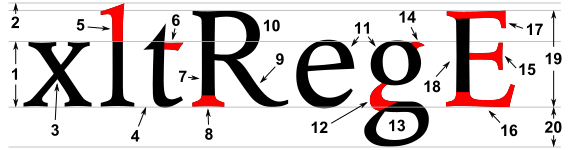
Линии
Через любую строку текста можно провести несколько воображаемых горизонтальных линий:
- Верхний край кегельной площадки — в металлическом наборе является верхней границей литеры. В компьютерных шрифтах верхний край кегельной площадки первой строки является верхним краем блока текста. В некоторых шрифтах, чаще всего декоративных, выносные элементы могут выходить за пределы верхнего края кегельной, однако такие выносные элементы требуют специальных инструкций для сопряжения с элементами верхней строки, во избежание наложений. Расстояние от верхнего до нижнего края кегельной площадки называется кеглем шрифта[1];
- Линия верхних выносных (2) — линия, проходящая через вершины верхних выносных элементов, если они унифицированы по высоте. В некоторых шрифтах может совпадать с линией прописных, но чаще — выше её[2];
- Линия прописных — линия, проходящая по верхней границе прописных букв[3]. Расстояние от базовой линии до линии прописных называется ростом прописных (19);
- Линия строчных — линия, проходящая по верхней границе строчных букв, не имеющих верхних выносных элементов и оптической компенсации[4]. Расстояние от базовой линии до верхней линии строчных называется ростом строчных (1);
- Базовая линия (линия шрифта) (4) — линия, проходящая по нижним границам букв, не имеющих нижних выносных элементов, свисаний и оптической компенсации[5]. Базовая линия одна для прописных и строчных букв. В вариативных шрифтах базовая линия остаётся статичной, однако вертикальные метрики могут динамически изменяться[6];
- Линия нижних выносных — линия, проходящая по нижнему краю нижних выносных элементов, если они унифицированы по высоте[7]. В современной типографике линии выносных элементов могут выступать как настраиваемые оси вариативности[8];
- Нижний край кегельной площадки — нижняя граница литеры;
- Кроме горизонтальных линий, важное значение имеет ось овала — линия, проходящая вдоль наибольшего диаметра овала, либо через наиболее тонкие участки штриха. Ось овала может быть вертикальной или наклонной[9].
Штрихи
- Основной штрих (штамб) (7) — наиболее толстый вертикальный или наклонный штрих в шрифтах, имеющих контраст[10]. В вариативных шрифтах его толщина динамически изменяется при помощи оси насыщенности (wght)[8];
- Соединительный штрих — более тонкий, чем основной, горизонтальный или наклонный штрих[11]. В вариативных шрифтах соотношение его толщины с основным штрихом также может динамически управляться[8].
Выносные элементы
- Верхний выносной элемент (5) — выносной элемент строчной буквы, выступающий вверх за линию строчных;
- Нижний выносной элемент — выносной элемент, свисающий ниже базовой линии;
- В вариативных шрифтах высота верхних и нижних выносных элементов может управляться через пользовательские оси вариативности, что позволяет адаптировать шрифт под конкретные задачи вёрстки[8].
Прочие элементы
- Вершина (апекс) (3) — соединение двух наклонных штрихов либо наклонного и вертикального штриха, образующее угол либо имеющее ровную площадку[12];
- Горизонтальный элемент (6) — штрих, расположенный поперёк вертикального штриха. Может быть соединён с ним по краям либо в середине[13];
- Овал — округлый элемент штриха замкнутой формы, например в буквах «О», «Ю». Ось овала может быть прямой или наклонной[14];
- Полуовал (10) — может быть как замкнутым и ограниченным с одной из сторон штрихом (в буквах «Р», «Б»), так и разомкнутым (например, в букве «З»)[15];
- Узел — соединение в одном месте нескольких штрихов[16];
- Перекладина (15) — Горизонтальный штрих примерно (оптически) на середине высоты букв[17];
- Кегельная площадка — в металлическом наборе — площадка на ножке литеры, на которой располагался отпечатываемый знак. В цифровом наборе кегельная площадка — абстрактный прямоугольник, очерченный вокруг знака[18];
- Концевой элемент — окончание штриха, не имеющее засечки[19];
- Нога (9) — Наклонный штрих, заканчивающийся засечкой или концевым элементом;
- Засечка (сериф) (8) — короткий штрих, перпендикулярный основному, расположенный на его конце[20]. В вариативных шрифтах её форма и толщина могут параметрически изменяться[21];
- Наплыв (11) — утолщение штрихов в овальных элементах, формирующее контраст шрифта и определяющее ось овала[22][23];
- Присоединение — штрих, соединяющий части глифа[24];
- Ухо (14) — элемент, характерный для строчной буквы «g» в некоторых начертаниях. Выглядит как небольшой отросток на овале[25];
- Капля — каплевидное окончание штриха[26];
- Петля (13) — нижний элемент строчной буквы «g» в некоторых начертаниях[27]. Как и овал, имеет замкнутую форму, но построен по другому принципу;
- Хвост — элемент глифа, плавный по форме, не заканчивающийся засечкой, и являющийся, как правило, выносным[28];
- Диакритические знаки — надстрочные и подстрочные элементы, модифицирующие значение букв, которые проектируются с учётом стилистического единства основного шрифта[29].
Пустое пространство
- Заплечики — пространство над и под очком литеры[30];
- Внутрибуквенный просвет — внутренняя часть знака, ограниченная со всех, или почти со всех сторон другими элементами знака[31]. В современных вариативных шрифтах его форма и размер динамически изменяются в зависимости от осей насыщенности, ширины и оптического размера;
- Апрош — боковое пространство знака слева и справа от его контура, формирующее межбуквенный пробел[32];
- Кернинг — избирательное изменение расстояния между конкретными парами символов. В вариативных шрифтах эти значения могут динамически интерполироваться[32][8].
Характеристики шрифта
- Рост строчных — высота от базовой линии до линии строчных[33];
- Рост прописных — высота от базовой линии до линии прописных[34];
- Рост шрифта — расстояние от основания литеры до печатающей поверхности. Имеет смысл только по отношению к шрифтам металлического набора, где эта величина стандартизирована и всегда равна 25,1012 мм[35];
- Очко шрифта — понятие, характеризующее рост строчных букв относительно размера литеры. Обычно не имеет величины, употребляются понятия «крупное очко» и «мелкое очко»[36];
- Контраст — характеристика различия толщин основных и соединительных штрихов шрифта[37]. В вариативных шрифтах возможно плавное управление контрастом через пользовательскую ось CNTR[38];
- Насыщенность — понятие, характеризующее отношение толщины основного штриха к кеглю шрифта[39]. В вариативных шрифтах она регулируется стандартной осью wght с диапазоном значений от 1 до 1000[40];
- Апертура — понятие, характеризующее угол среза концов полуовала в буквах, подобных «с»[41]. В вариативных шрифтах может выступать как динамический параметр для улучшения читаемости[8];
- Ширина начертания — характеристика, позволяющая изменять ширину от узких до широких знаков (ось wdth)[21];
- Наклон и курсивность — характеристики, разделяющие механический наклон (ось slnt) и истинный курсив с изменением конструкции знаков (ось ital)[21];
- Оптический размер — характеристика, адаптирующая контраст и детали шрифта под конкретный кегль (ось opsz)[42].
Вариативные шрифты и динамика
В 2016 году компаниями Adobe, Apple, Google и Microsoft был представлен формат OpenType Variable Fonts (вариативные шрифты), ставший фундаментальным сдвигом в развитии типографики. В отличие от традиционных статичных шрифтов, где каждое начертание требует отдельного файла, новая технология позволяет объединить множество стилей в одном файле. Это достигается за счёт использования «осей вариативности» — заданных дизайнером диапазонов изменения определённых характеристик шрифта, вдоль которых происходит плавная интерполяция формы знаков[8].[21]
Технология предоставляет возможность динамического изменения формы шрифта в реальном времени. Это позволяет создавать адаптивную и интерактивную типографику, которая способна мгновенно реагировать на действия пользователя или параметры окружающей среды. Например, начертание может автоматически менять насыщенность при наведении курсора, изменять ширину при прокрутке страницы или корректировать контрастность в зависимости от показаний датчиков устройства[43]. Подобная отзывчивость превращает текст из статичного элемента в функциональную часть интерфейса, улучшая читаемость и визуальный опыт.